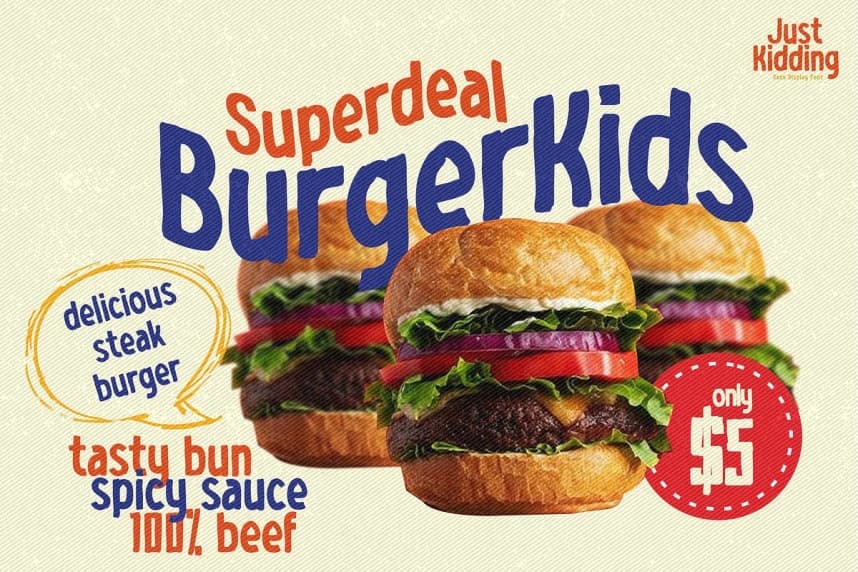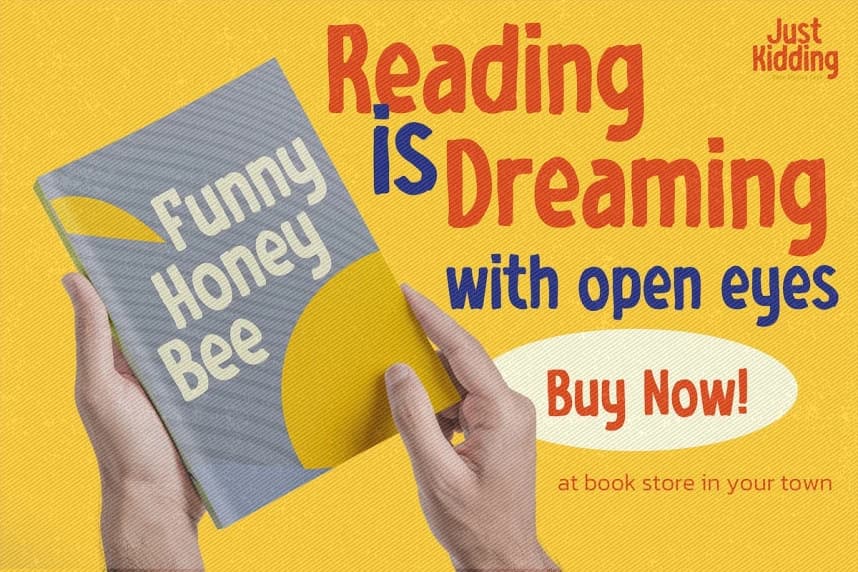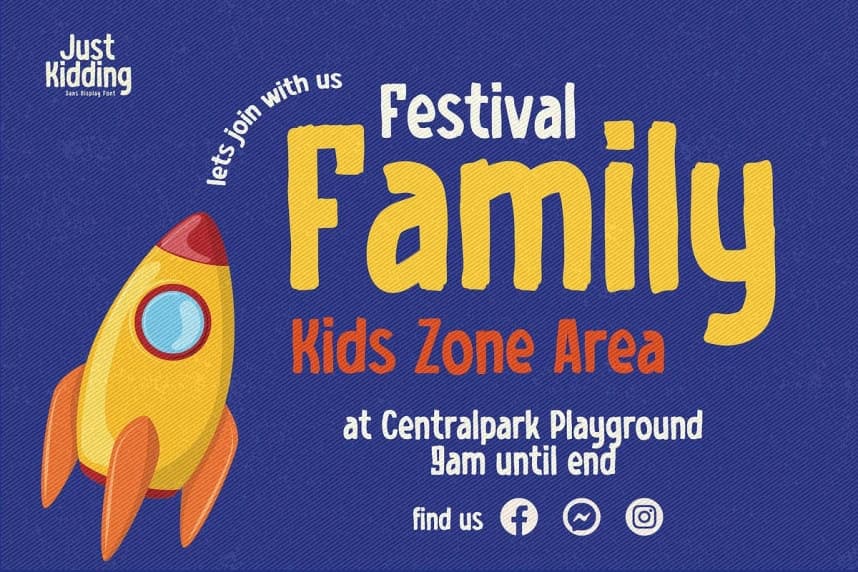
Just Kidding Font, Sans Display Font'tur. Bu font otantik olup gündelik ve hızlı yazılmıştır. Sonra tarandı ve dikkatle vektör formatına dönüştürüldü. Bu el yapımı font, tasarımınıza her detaya güzel ve doğal bir dokunuş katacak.
Just Kidding Font, Sans Display Font'tır. Bu font, gündelik ve hızlı bir biçimde yazılmış özgün bir yazı tipidir. Ardından taranmış ve dikkatlice vektör formatına dönüştürülmüştür. Bu el yapımı font, tasarımınıza her detaya güzel, doğal bir dokunuş katacaktır.